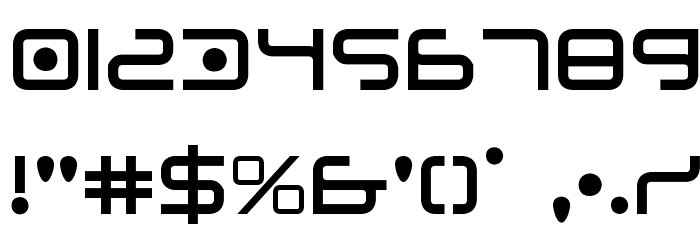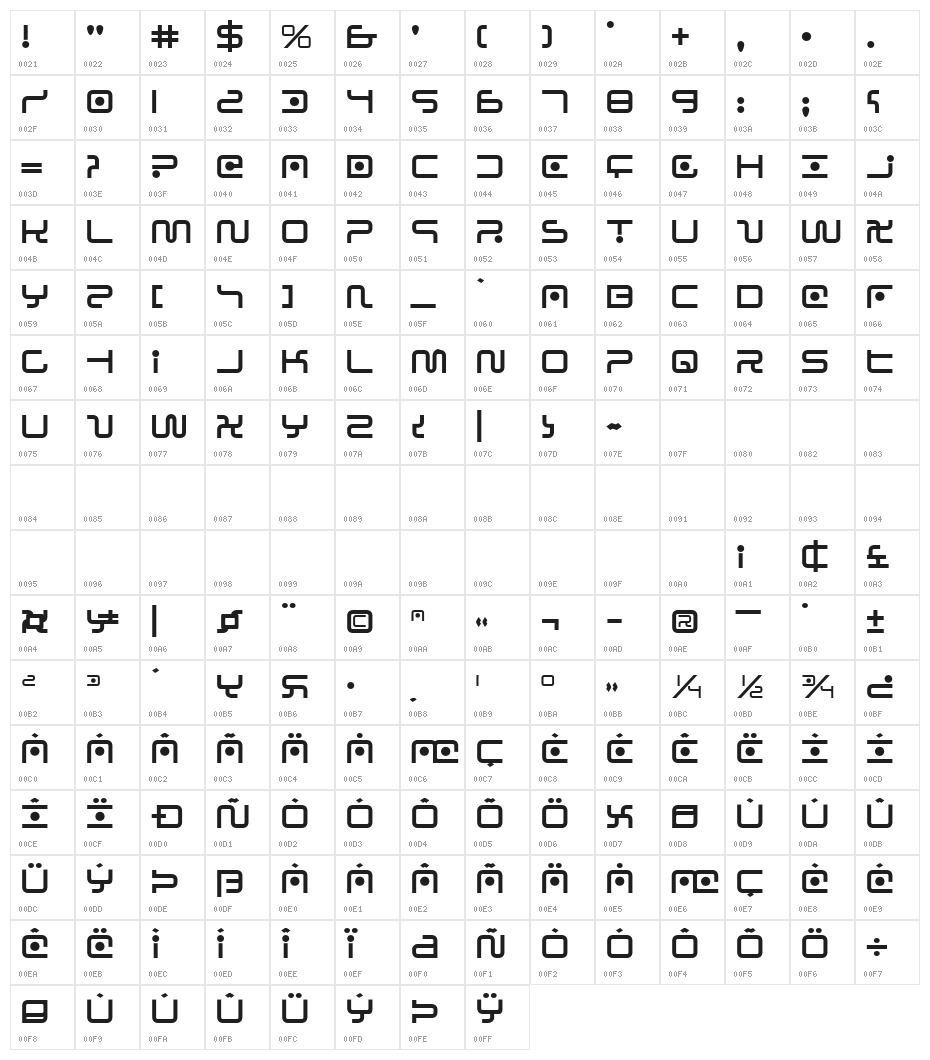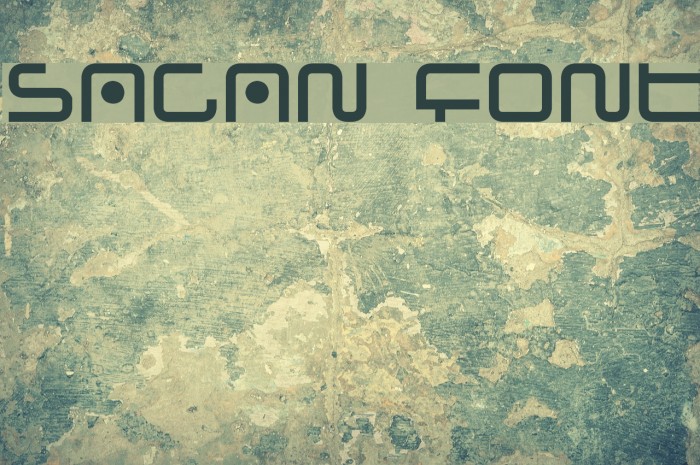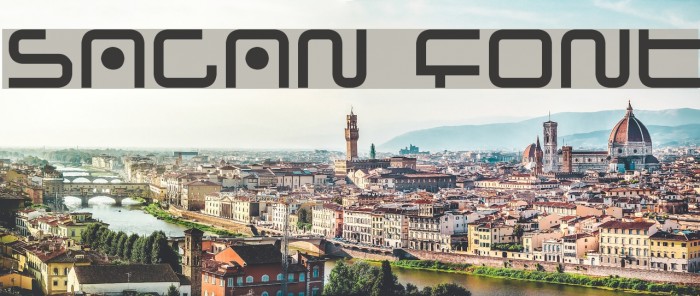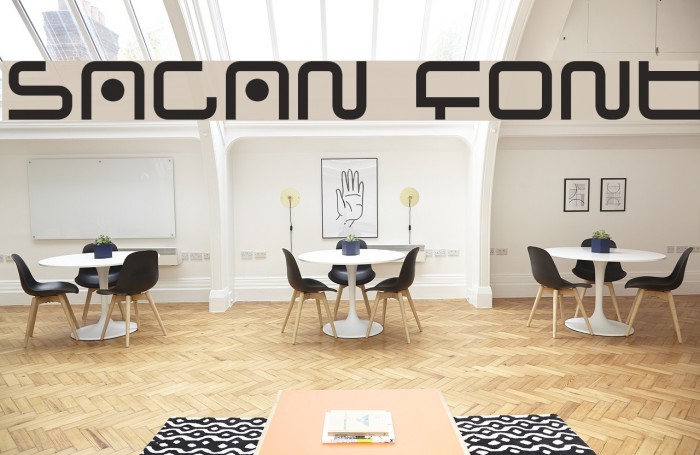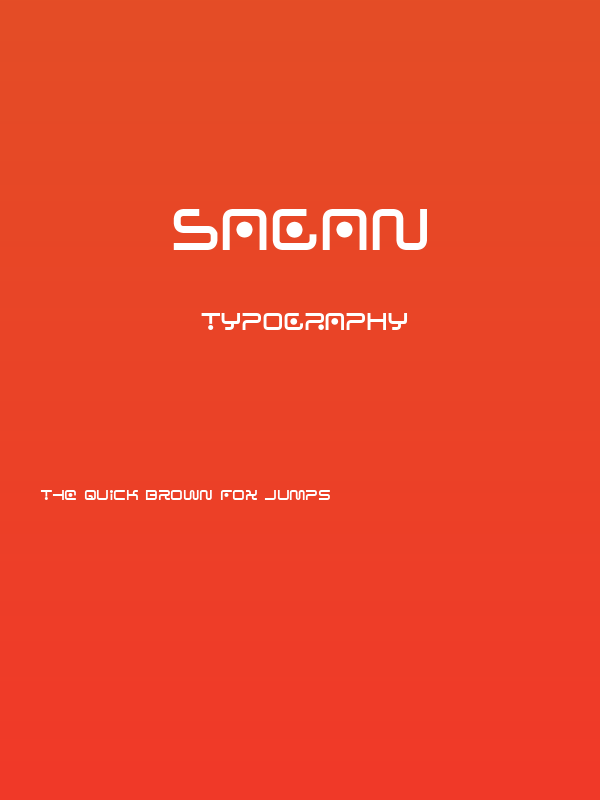
Sagan Font
✎ Sci-fi
| Kategorien | Sci-fi |
| Anwendungsfall | Logos, Headlines, Digital interfaces |
| Vorgeschlagene Projekte | Ideal for sci-fi movie posters, tech company logos, video game interfaces, and digital art projects. |